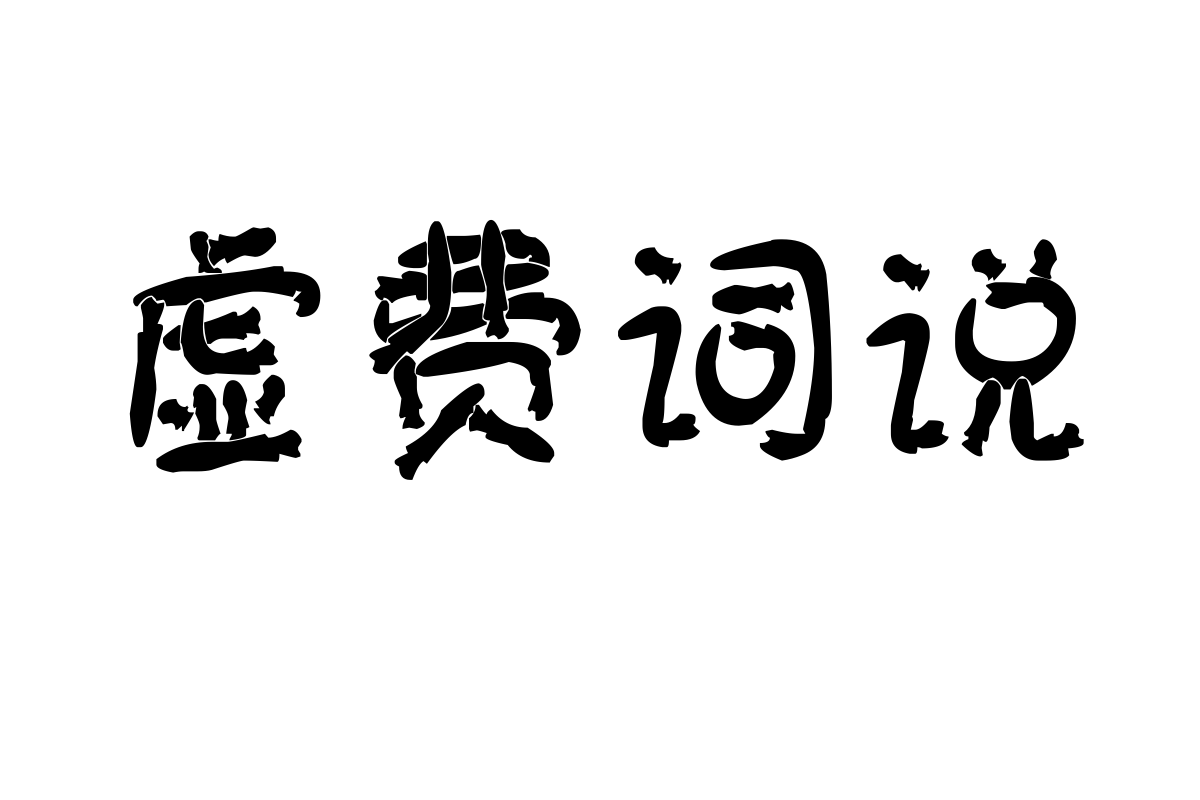
汉标鬼符体是一种具有独特风格的中文字体,它结合了传统汉字的书写特点和现代设计元素,创造出独特的视觉效果。这种字体的特点是字形结构紧凑,笔画粗细不一,给人一种古朴而富有张力的感觉。
汉标鬼符体的字体特点如下:
1. 字形结构紧凑:汉标鬼符体的字形结构紧凑,笔画分布均匀,使得整体视觉效果更加和谐。
2. 笔画粗细不一:汉标鬼符体的笔画粗细不一,既有粗犷豪放的特点,又有细腻精致的感觉,使得整体视觉效果更加丰富。
3. 古朴风格:汉标鬼符体采用了传统的汉字书写风格,保留了汉字的原始韵味,给人一种古朴典雅的感觉。
4. 张力十足:汉标鬼符体的笔画粗细不一,使得整体视觉效果充满张力,具有很强的视觉冲击力。
5. 现代设计元素:虽然汉标鬼符体保留了传统汉字的风格,但它也融入了一些现代设计元素,使得整体视觉效果更加时尚。
总之,汉标鬼符体是一种具有独特风格和强烈视觉冲击力的中文字体,它结合了传统汉字的书写特点和现代设计元素,创造出独特的视觉效果。